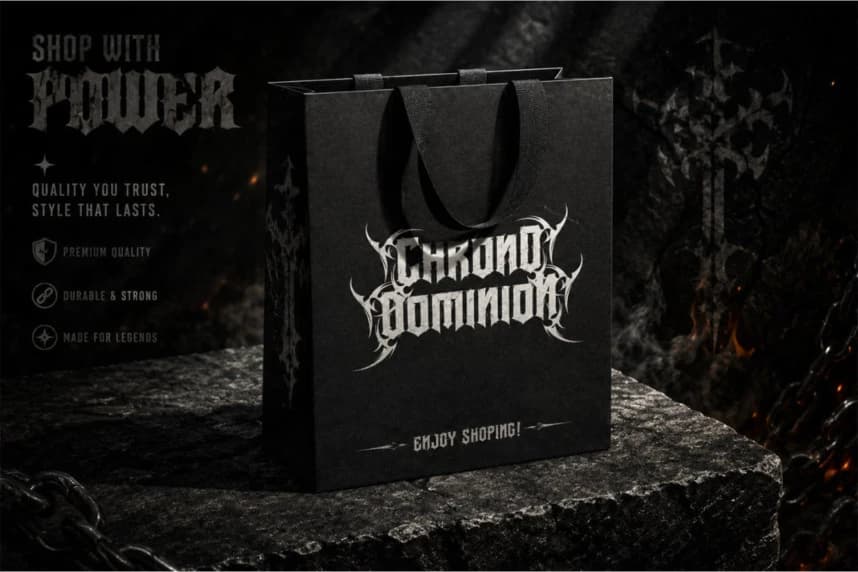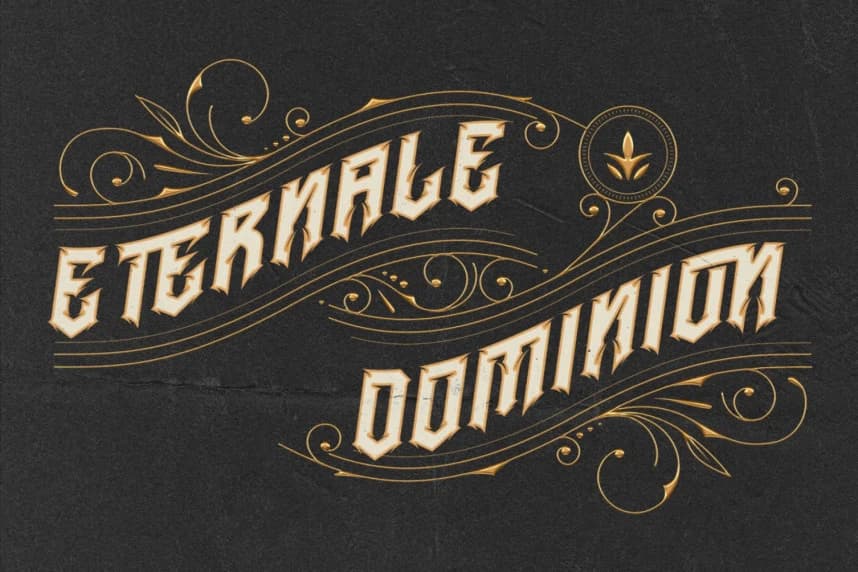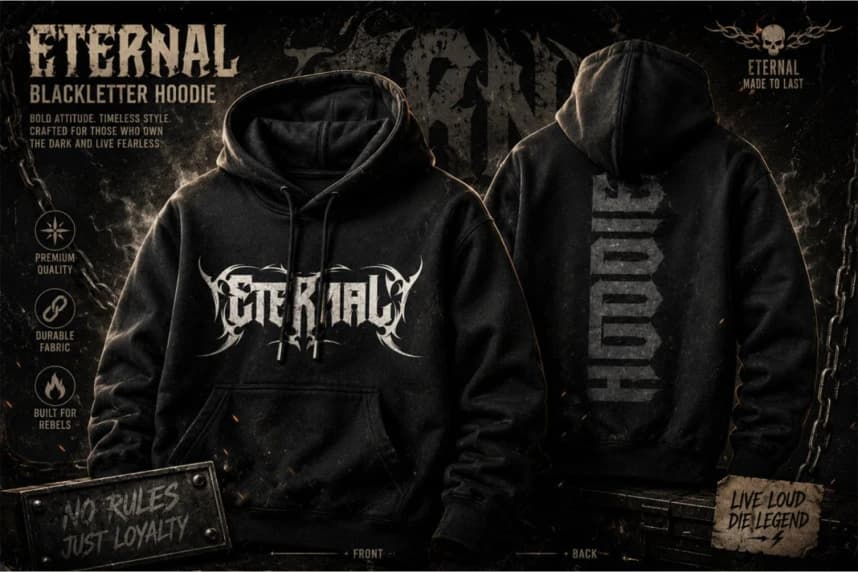
Istarot Yazı Tipi
Istarot Font, karanlık zarafetle yoğrulmuş, son derece keskin detaylara ve baskın bir gotik varlığa sahip olan güçlü bir blackletter yazı tipidir. Ortaçağ mimarisinden, okült sembolizmden ve aşırı metal estetiğinin ham enerjisinden esinlenmiştir.
Istarot Font, karanlık zarafetle, keskin hatlarla ve baskın bir gotik duruşla üretilen sert bir blackletter yazı tipidir. Ortaçağ mimarisinden, okült sembolizminden ve extreme metal estetiğinin ham enerjisinden ilham almıştır.